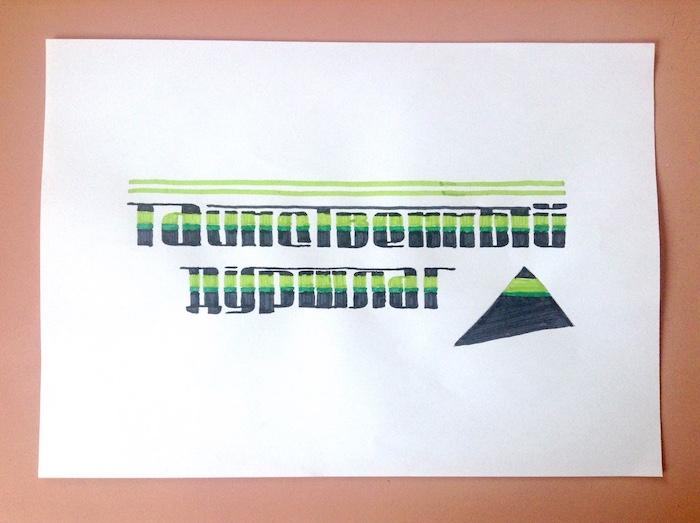
Буква «Ы» — интересна. Вы уверены, что её будут распознавать?
@TH3_C0N-MAN: изменил для этого шрифта, эта форма не везде уместна, но здесь выглядит отлично. Ещё здесь довольно странная F, которая обычно не имеет засечки на конце горизонтального штриха, но @zephram её здесь сделал.
Кстати, я всегда считал, что было бы лучше, если бы буква: «ы» выглядела как: «ъı». Она твёрдая, прав? Так почему у неё мягкий знак? (Я знаю, что это не фактически мягкий знак. :D )
А пожалуйста, не могли бы вы посмотреть на букву: «з» в моём последнем шрифте? Она действительно разная от нормальной. Мне просто хочется мнение реального русскоязычного.
Вот рисование, которое я нарисовал глазами от руки. Надеюсь, что вам нравится.
@TH3_C0N-MAN: Вау, я в восторге! (Но верней было написать: "Вот рисунок, который я нарисовал на глаз.")